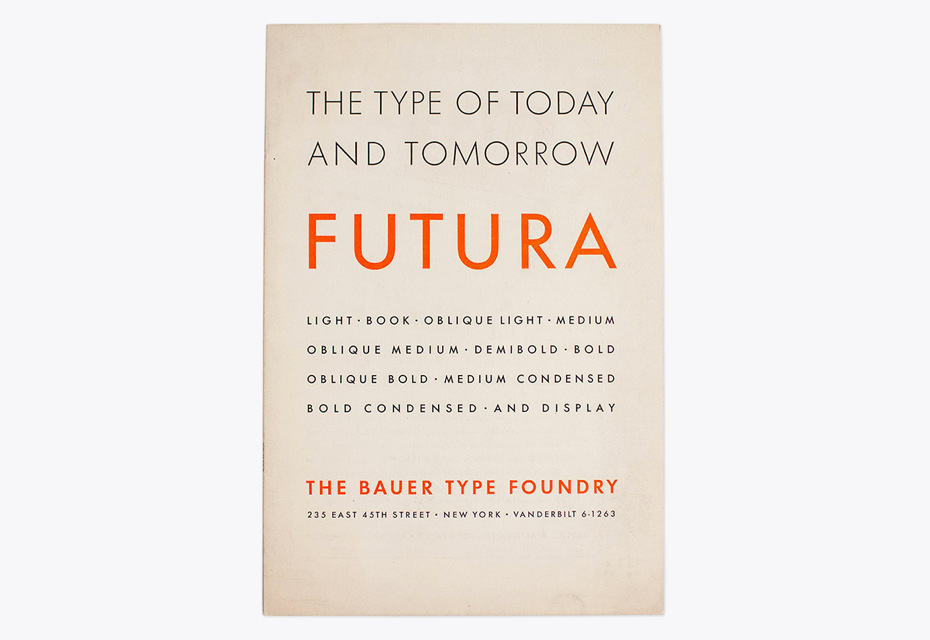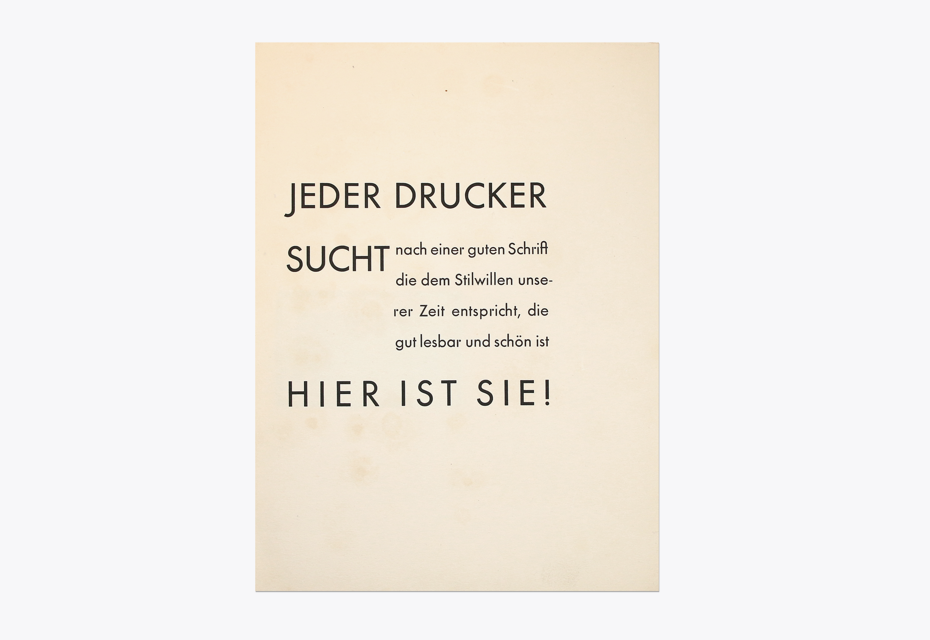
Краткая история геометрических гротесков в немецкой культуре
Крат­кая ис­то­рия гео­мет­ри­че­ских гро­те­сков
в не­мец­кой куль­ту­ре
Шриф­ты вы­ра­жа­ют дух сво­е­го вре­ме­ни. Бур­ные два­дца­тые XX ве­ка по­да­ри­ли ми­ру це­лый ряд от­кры­тий в ис­кус­стве и на­у­ке, то­гда же про­изо­шло ин­тен­сив­ное раз­ви­тие ин­же­нер­ной мыс­ли в Гер­ма­нии. Всё это на­шло от­ра­же­ние и в «но­вой ти­по­гра­фи­ке». Меж­ду 1925 и 1930 го­да­ми окон­ча­тель­но сфор­ми­ро­вал­ся прин­ци­пи­аль­но иной взгляд на шриф­т и со­вре­мен­ную ти­по­гра­фи­ку: шриф­ты ста­ли «стро­ить», что да­ло им­пульс раз­ви­тию гео­мет­ри­че­ских гро­те­сков.
1926 го­ду в Гер­ма­нии про­ис­хо­дит ряд важ­ных со­бы­тий. Бы­ла по­стро­е­на бер­лин­ская ра­дио­баш­ня с об­зор­ной пло­щад­кой на вы­со­те 125 мет­ров, от­крыв­шая зри­те­лю но­вый вид на ме­га­по­лис. В том же го­ду гол­ланд­ский ар­хи­тек­тор и пре­по­да­ва­тель Ба­у­ха­у­за Март Ст­ам (Martinus Stam, 1899–1986) спро­ек­ти­ро­вал кон­струк­цию кон­соль­но­го сту­ла, со­бран­но­го из сталь­ных тру­бок (по су­ти, пер­вый стул в ис­то­рии, не име­ю­щий зад­них но­жек) и об­ла­да­ю­ще­го по­движ­ной кон­струк­ци­ей. В это же вре­мя ар­хи­тек­тор Людвиг Мис ван дер Роэ, вер­нув­шись из Штут­гар­та — где он уви­дел впер­вые мо­дель сту­ла Ста­ма — лёг­кой ру­кой усо­вер­шен­ство­вал его кон­струк­цию и в 1927 го­ду по­лу­чил па­тент на сво­й ва­ри­ан­т так на­зы­ва­е­мо­го сту­ла Freischwinger (са­мо­ба­лан­си­ру­ю­щий­ся кон­соль­ный стул). Эта кон­струк­ция из сталь­ных дуг пред­ла­га­ла усев­ше­му­ся в не­го при­ят­ную эр­го­но­мич­ную ам­пли­ту­ду по­ка­чи­ва­ния.
1 — кон­соль­ный сту­л Kragstuhl по мо­де­ли Мар­та Ста­ма из кол­лек­ции ди­зайн-му­зея Vitra; 2 — ва­ри­ант мо­де­ли са­мо­ба­лан­си­ру­ю­ще­го­ся кон­соль­но­го сту­ла Freischwinger Людви­га Ми­са ван дер Роэ. Из вос­по­ми­на­ний Сер­ги­у­са Рю­ген­бер­га (Sergius Ruegenberg, 1903–1996), од­но­го из со­труд­ни­ков Ми­са ван дер Роэ: «В но­я­бре 1926 го­да Мис вер­нул­ся из Штут­гар­та и рас­ска­зал нам о сту­ле Ст­ама и его иде­ях. Тут же на ви­сев­шей ря­дом дос­ке он на­ри­со­вал стул Ст­ама со сло­ва­ми: „Если из­ба­вить­ся от этих урод­ли­вых муфт (а кар­кас пер­вой мо­де­ли сту­ла Ста­ма был сде­лан из пря­мых труб, со­единён­н­ных муф­та­ми — прим. ред.) и за­ме­нить углы на ду­ги, он пре­об­ра­зит­ся“», — и од­ним дви­же­ни­ем на­ри­со­вал ря­дом эс­киз но­во­го сту­ла«. © Фо­то: Malik Gallery Collection, про­из­во­ди­те­ль объ­ек­тов ме­бе­ли с 90-лет­ней ис­то­ри­ей, при­дер­жи­ва­ю­щий­ся при­нци­пов Ба­у­ха­у­за.
В этот же пе­ри­од, в 1925–1926 го­дах, в Бер­ли­не под ру­ко­вод­ством ар­хи­тек­то­ра Бру­но Та­у­та (Bruno Taut, 1880–1938) на­ча­лось стро­и­тель­ство но­вых, со­вре­мен­ных жи­лых ком­плек­сов: посёл­ка «Хи­жи­на дя­ди То­ма» (Onkel Toms Hütte) и ми­кро­рай­о­на Ху­фай­зен (Hufeisensiedlung, нем. посёлок «Под­ко­ва»). Оба рай­о­на спро­ек­ти­ро­ва­ны как боль­шие жи­лые ком­плек­сы, вы­стро­ен­ные длин­ны­ми объ­единён­ны­ми меж­ду со­бой сек­ци­я­ми, со мно­же­ством ма­лень­ких око­шек раз­ных раз­ме­ров. Опыт воз­ве­де­ния этих ми­кро­рай­о­нов в Бер­ли­не ста­л важ­ной ве­хой в ис­то­рии гра­до­стро­и­тель­ства и од­ним из пер­вых при­ме­ров ре­ше­ния острой про­бле­мы не­хват­ки до­ступ­но­го жи­лья. То­гда же сту­ден­ты Ба­у­ха­у­за пе­ре­ез­жа­ют в Дес­сау, в но­вое зда­ние шко­лы, спро­ек­ти­ро­ван­ное Валь­те­ром Гро­пи­у­сом. Све­то­про­зрач­ный фа­сад это­го зда­ния прак­ти­че­ски сра­зу стал яв­ле­ни­ем зна­ко­вым, как и над­пись B-A-U-H-A-U-S на фа­са­де из при­ми­тив­ных гео­мет­ри­че­ских букв, по­стро­ен­ных по мо­дуль­ной сет­ке. Ба­зо­вые гео­мет­ри­че­ские фор­мы (квад­рат, тре­уголь­ник и круг) к то­му мо­мен­ту уже бы­ли по­всю­ду: они ис­поль­зо­ва­лись в ар­хи­тек­ту­ре, про­мыш­лен­но­сти, гра­фи­че­ском ди­зай­не и, ко­неч­но же, в над­пи­сях и бук­вах.
В 1925 го­ду в спе­ци­аль­ном вы­пус­ке не­мец­ко­го жур­на­ла «Ти­по­гра­фи­че­ские ве­до­мо­сти» (Typographische Mitteilungen), оза­глав­лен­ном «Эле­мен­тар­ная ти­по­гра­фи­ка» (Elementare Typographie), бы­ла опуб­ли­ко­ва­на ста­тья Яна Чи­холь­да, в ко­то­рой он опи­сал свои взгля­ды на «но­вую ти­по­гра­фи­ку». Чи­хольд ут­вер­ждал, что но­вая ти­по­гра­фи­ка сле­ду­ет за иде­я­ми функ­ци­о­наль­но­сти, от­ри­цая из­бы­точ­ные ор­на­мен­ты и ис­поль­зуя в ка­че­стве основ­ных гра­фи­че­ских эле­мен­тов ли­нии и про­стей­шие гео­мет­ри­че­ские фор­мы. В четвёр­том пунк­те сво­е­го ма­ни­фе­ста Чи­хольд пи­сал: «В ка­че­стве основ­но­го шриф­та дол­жен ис­поль­зо­вать­ся гро­теск в лю­бых сво­их про­яв­ле­ни­ях». В те го­ды мно­гие сло­во­лит­ни стре­ми­лись со­зда­вать шриф­ты, осно­вы­ва­ясь на ба­зо­вых гео­мет­ри­че­ских фор­мах, ко­то­рые не толь­ко удо­вле­тво­ря­ли бы по­треб­но­сти но­вой ти­по­гра­фи­ки, но и ви­зу­аль­но со­от­вет­ство­ва­ли ду­ху вре­ме­ни.
Не­боль­шие вре­мен­ные ин­тер­ва­лы меж­ду вы­хо­да­ми та­ких шриф­тов на­гляд­но по­ка­зы­ва­ют, что в кон­це 20-х — на­ча­ле 30-х го­дов су­ще­ство­ва­ло мно­же­ство «шриф­тов сво­е­го вре­ме­ни». Да­лее мы рас­ска­жем о не­сколь­ких ори­ги­наль­ных гео­мет­ри­че­ских шриф­тах ме­тал­ли­че­ской эпо­хи, а так­же об их пер­вых ре­кон­струк­ци­ях 1970-х го­дов, о не­ко­то­рых ин­тер­пре­та­ци­ях по­сле­ду­ю­щих лет и со­вре­мен­ном раз­ви­тии это­го по­пу­ляр­но­го в на­ши дни жан­ра.
Гро­те­ски и лет­те­ринг в Ба­у­ха­у­зе
По­дав­ля­ю­щее боль­шин­ство идей Ба­у­ха­у­за бы­ло осно­ва­но на эле­мен­тар­ных гео­мет­ри­че­ских прин­ци­пах, ко­то­рых при­дер­жи­вал­ся и Гер­берт Бай­ер (Herbert Bayer, 1900–1985), сту­дент Ба­у­ха­у­за, впо­след­ствии пре­по­да­ва­тель ти­по­гра­фи­ки там же. Имен­но он спро­ек­ти­ро­вал над­пись для фа­са­да но­во­го зда­ния Ба­у­ха­у­за, а в 1925 го­ду за­ни­мал­ся раз­ра­бот­кой «уни­вер­саль­но­го» ал­фа­ви­та, из­вест­но­го как Universalschrift. Бай­ер пы­тал­ся при по­мо­щи цир­ку­ля и ли­ней­ки со­здать шрифт, у ко­то­ро­го не бы­ло бы раз­де­ле­ния на строч­ные и про­пис­ные зна­ки. Стро­го го­во­ря, это был не шрифт, а лишь на­бор ал­фа­вит­ных зна­ков. Меж­ду 1925 и 1930 го­да­ми, Бай­ер не­сколь­ко раз пе­ре­ри­со­вы­вал его, а в сво­ей ста­тье «В по­ис­ках но­во­го шриф­та» (Versuch einer neuen Schrift) для про­фес­си­о­наль­но­го жур­на­ла Offset-, Buch- und Werbekunst он пред­ста­вил бо­лее на­сы­щен­ное на­чер­та­ние в нор­маль­ном и за­ужен­ном ва­ри­ан­тах, из­вест­ное се­го­дня как «Ал­фа­вит» Бай­е­ра (Bayer’s Alphabet). Бук­вы Бай­е­ра бы­ли стро­го гео­мет­рич­ны, что за­труд­ня­ло их чте­ние в мел­ких кеглях.
Не­ко­то­рые кол­ле­ги Бай­е­ра то­же экс­пе­ри­мен­ти­ро­ва­ли в об­ла­сти гео­мет­ри­че­ских шриф­тов. Ко­неч­но, са­ма идея гео­мет­ри­че­ских гро­те­сков не при­над­ле­жа­ла Ба­у­ха­у­зу: к это­му мо­мен­ту на про­тя­же­нии де­ся­ти­ле­тий по­хо­жие зна­ки ис­поль­зо­ва­лись ху­дож­ни­ка­ми на фа­са­дах и вы­вес­ках ма­га­зи­нов. Од­на­ко по-на­сто­я­ще­му по­пу­ляр­ны­ми гео­мет­ри­че­ские гро­те­ски ста­ли имен­но то­гда, ко­гда пре­по­да­ва­те­ли Ба­у­ха­у­за на­ча­ли ис­поль­зо­вать их в учеб­ной про­грам­ме. На­при­мер, Йост Шмидт, ко­то­рый на­ря­ду со шриф­та­ми без за­се­чек, брус­ко­вы­ми шриф­та­ми и но­во­стиль­ной ан­ти­к­вой на­ри­со­вал мо­дуль­ный гео­мет­ри­че­ский гро­теск. В 1926 го­ду бы­ли опуб­ли­ко­ва­ны эс­ки­зы Тра­фа­рет­но­го шриф­та (Schablonenschrift) Йо­зе­фа Аль­бер­са (Josef Albers, 1888–1976), осно­ван­но­го на сет­ке и по­стро­ен­но­го из квад­ра­тов, тре­уголь­ни­ков, кру­гов и их сег­мен­тов. Пять лет спу­стя его упро­сти­ли, ис­поль­зо­вав в ка­че­стве осно­вы лишь де­сять эле­мен­тов (сре­ди них уже не бы­ло тре­уголь­ных форм), и он стал из­ве­стен как Ком­би­на­тор­ный шрифт (Kombinationsschrift).
Впро­чем, ни один из так на­зы­ва­е­мых шриф­тов Ба­у­ха­у­за не был от­лит в ме­тал­ле. Каж­дый раз все зна­ки ри­со­ва­лись вруч­ную, а если нуж­но бы­ло пе­ча­тать боль­шие объ­ё­мы тек­ста, при­ме­ня­лись дру­гие, не гео­мет­ри­че­ские, но близ­кие по ду­ху гро­те­ски. Ча­ще все­го в сво­их пла­ка­тах Ба­у­ха­уз ис­поль­зо­вал два на­бор­ных шриф­та: Venus сло­во­лит­ни Bauersche Gießerei, на­по­ми­на­ю­щий о сти­ле ар-де­ко, с ха­рак­тер­ны­ми за­вы­шен­ны­ми та­ли­я­ми зна­ков, и шрифт под на­зва­ни­ем Grotesk не­мец­кой сло­во­лит­ни J.G. Schelter & Giesecke (по­это­му се­го­дня его ча­сто на­зы­ва­ют Schelter Grotesk). Вряд ли в Ба­у­ха­у­зе поль­зо­ва­лись ка­ки­ми-ли­бо гео­мет­ри­че­ски­ми шриф­та­ми, вы­пу­щен­ны­ми в кон­це 1920-х. Един­ствен­ным из­вест­ным ис­клю­че­ни­ем яв­ля­ет­ся тра­фа­рет­ное на­чер­та­ние Futura Black, по­хо­жее на тра­фа­рет­ный шрифт Аль­бер­са и ис­поль­зо­ван­ное на об­лож­ке жур­на­ла Bauhausbücher No.12, вы­пу­щен­но­го в 1930 го­ду.
Erbar-Grotesk, 1926
Пер­вым от­ли­тым в ме­тал­ле не­мец­ким гео­мет­ри­че­ским гро­те­ском стал Erbar-Grotesk, вы­пу­щен­ный сло­во­лит­ней Ludwig & Mayer в 1926 го­ду. Его со­зда­тель Якоб Эр­бар (Jakob Erbar, 1878–1935) взял в ка­че­стве ба­зо­во­го эле­мен­та сво­е­го шриф­та круг (от­ме­тим прак­ти­че­ски иде­аль­но круг­лую фор­му про­пис­ной бук­вы О).
В сво­их пер­вых шриф­то­вых ка­та­ло­гах ком­па­ния пи­са­ла, что «этот креп­кий гро­теск лишён вся­ких глу­по­стей» и ко­гда-ни­будь он вы­тес­нит из на­бор­но­го це­ха «ста­рые бес­ха­рак­тер­ные шриф­ты». В пе­ри­од с 1926 по 1930 го­д Erbar-Grotesk вы­рос в бес­пре­це­дент­но боль­шое шриф­то­вое се­мей­ство со мно­же­ством на­чер­та­ний: от свет­ло­го до жир­но­го с со­от­вет­ству­ю­щи­ми кур­си­ва­ми, уз­ки­ми на­чер­та­ни­я­ми, а так­же не­сколь­ки­ми ори­ги­наль­ны­ми кон­тур­ны­ми на­чер­та­ни­я­ми для за­го­лов­ков и бук­виц. По­зд­нее по­яви­лись шриф­ты Lucina, Lichte fette Grotesk, Lumina и Lux, ко­то­рые бы­ли сво­е­го ро­да «род­ствен­ни­ка­ми» се­мьи Erbar-Grotesk. Ха­рак­тер­ны­ми чер­та­ми Erbar-Grotesk яв­ля­ют­ся двух­част­ная строч­ная «а» и вы­ра­зи­тель­ная ли­га­ту­ра «ß», у ко­то­рой есть и верх­ний, и ниж­ний вы­нос­ные эле­мен­ты. От­го­лос­ки шриф­та Erbar-Grotesk и по сей день мож­но встре­тить на мно­гих улич­ных ука­за­те­лях в за­пад­ной ча­сти Бер­ли­на.
Futura, 1927
В 1927 го­ду сло­во­лит­ня Bauersche Gießerei вы­пу­сти­ла шрифт Futura, спро­ек­ти­ро­ван­ный Пау­лем Рен­не­ром. Боль­шой по­пу­ляр­но­стью шрифт обя­зан не толь­ко сво­е­му име­ни, но и ре­клам­но­му сло­га­ну Die Schrift unserer Zeit (нем. «шрифт на­ше­го вре­ме­ни»), по­явив­ше­му­ся бла­го­да­ря из­да­те­лю Яко­бу Хегне­ру (Jakob Hegner, 1882–1962). Ко­неч­но, ут­вер­жде­ние, что Futura бы­ла един­ствен­ным шриф­том сво­е­го вре­ме­ни, че­рес­чур са­мо­на­де­я­нно — шриф­то­вой ди­зайн был так­ же раз­но­об­ра­зен, как и ар­хи­тек­ту­ра или про­мыш­лен­ный ди­зайн, и, ко­неч­но, су­ще­ство­вал це­лый ряд гео­мет­ри­че­ских гро­те­сков, осно­ван­ных на схо­жих кон­цеп­ци­ях и иде­ях.
По­сле вы­хо­да шриф­та Futura в 1927 го­ду бы­ло мно­го спо­ров, по­вли­ял ли на не­го Erbar-Grotesk или, воз­мож­но, всё бы­ло ров­но на­о­бо­рот. Из­вест­но, что Па­уль Рен­нер за два го­да до по­яв­ле­ния Фу­ту­ры (в 1925 го­ду) пред­ста­вил свои шриф­то­вые идеи на лек­ции в Кёльн­ской ака­де­мии изоб­ра­зи­тель­но­го и при­клад­но­го ис­кус­ства (Kölner Werkschule), где в то вре­мя пре­по­да­вал Якоб Эр­бар. Сам же Эр­бар ут­вер­жда­л, что на­чал про­ек­ти­ро­ва­ние сво­е­го шриф­та не­сколь­ки­ми го­да­ми ра­нее. Есть и дру­гой по­вод для спо­ров: про­пис­ные бук­вы шриф­та Futura уз­на­ют­ся в так на­зы­ва­е­мом Kramer-Grotesk ар­хи­тек­то­ра Фер­ди­нан­да Кра­ме­ра (Ferdinand Kramer, 1898–1985) — од­но­го из кол­лег Рен­не­ра по Шко­ле изящ­ных ис­кусств Франк­фур­та. Кра­мер офор­мил вы­вес­ку и вит­ри­ны ма­га­зи­на гео­мет­ри­че­ски­ми бук­ва­ми, ко­то­рые и счи­та­ют­ся пред­те­чей шриф­та Futura.
Идея Рен­не­ра вос­хо­ди­ла к ло­ги­ке зна­ков рим­ско­го мо­ну­мен­таль­но­го пись­ма, ко­то­рые в сво­ей осно­ве име­ли от­но­ше­ния гео­мет­ри­че­ских фор­м: кру­га, квад­ра­та и тре­уголь­ни­ка, этот приём ис­поль­зу­ет­ся и в по­стро­е­нии про­пис­ных букв шриф­та Futura. Как и в рим­ском мо­ну­мен­таль­ном, ши­ри­ны про­пис­ных у Фу­ту­ры за­мет­но раз­нят­ся: O и G прак­ти­че­ски иде­аль­но круг­лые, в то вре­мя как E, F и L впи­са­ны в по­ло­ви­ну квад­ра­та. Не­смот­ря на то что гео­мет­ри­я бы­ла по­пу­ляр­на, шрифт Рен­не­ра силь­но от­ли­чал­ся от экс­пе­ри­мен­тов с цир­ку­лем и ли­ней­кой в Ба­у­ха­у­зе. В ран­них вер­си­ях строч­ные a, g, m, n, u и r в шриф­те Futura прин­ци­пи­аль­но гео­мет­рич­ны­, но впо­след­ствии они бы­ли при­ве­де­ны к бо­лее при­выч­ным шриф­то­вым фор­мам.
В то вре­мя боль­шин­ство шриф­тов вы­пус­ка­лось в нор­маль­ном и жир­ном на­чер­та­ни­ях с со­от­вет­ству­ю­щи­ми кур­си­ва­ми, но для Фу­ту­ры бы­ла раз­ра­бо­та­на своя вну­ши­тель­ная си­сте­ма на­чер­та­ний: mager (свет­лое), Buchschrift (ре­гу­ляр­ное, до­слов­но — книж­ное), halbfett (по­лу­жир­ное), dreiviertelfett (бук­валь­но жир­ный на ¾, по­зд­нее по­лу­чив­ший в ан­гло­языч­ной си­сте­ме на­зва­ние demi bold) и fett (жир­ное), каж­дое чуть плот­нее пре­ды­ду­ще­го. На­чер­та­ние Buchschrift пред­на­зна­ча­лось для на­бо­ра длин­ных тек­стов, и шрифт ис­поль­зо­вал­ся в книж­ной про­дук­ции всех ви­дов.
В гео­мет­ри­че­ских гро­те­сках ча­сто «за­плы­ва­ют» ме­ста сты­ков основ­но­го и при­мы­ка­ю­ще­го штри­хов, и, что­бы тол­щи­ны бы­ли оп­ти­че­ски оди­на­ко­вы­ми, их при­хо­дит­ся кор­рек­ти­ро­вать, об­лег­чая штри­хи. Это хо­ро­шо вид­но в жир­ных на­чер­та­ни­ях Фу­ту­ры, где бы­ло при­ня­то боль­шое ко­ли­че­ство ком­про­мисс­ных ре­ше­ний: штри­хи, при­мы­ка­ю­щие к основ­ным, силь­но за­уже­ны, не­ко­то­рые про­пис­ные зна­ки по­те­ря­ли острые на­вер­шия (со­еди­не­ние двух штри­хов в верх­ней ча­сти бук­вы, на­при­мер у A и M), ко­то­рые яв­ля­лись од­ной из глав­ных осо­бен­но­стей свет­лых на­чер­та­ний, из­ме­ни­лась сте­пень от­кры­то­сти строч­ной e, — всё это со­зда­ёт ощу­ще­ние не­ко­то­рой не­по­сле­до­ва­тель­но­сти об­ще­го ди­зай­на.
И тем не ме­нее Futura до сих пор остаёт­ся са­мым по­пу­ляр­ным гео­мет­ри­че­ским гро­те­ском то­го вре­ме­ни. От­ча­сти это про­изо­шло бла­го­да­ря ак­тив­ной меж­ду­на­род­ной тор­го­вле сло­во­лит­ни Bauer Type Foundry (Bauersche Gießerei). И фра­за ху­до­же­ствен­но­го кон­суль­тан­та Bauer Ген­ри­ха Йо­ста (Heinrich Jost, 1889–1948) в од­ной из пуб­ли­ка­ций 1928 го­да под­чёр­ки­ва­ла ре­ши­тель­ность этой ком­па­нии: «Фу­ту­ра долж­на спо­соб­ство­вать раз­ви­тию „эле­мен­тар­ной ти­по­гра­фи­ки“, на­пра­вив её в но­вое русло».
Kabel, 1928
Вско­ре по­сле вы­пус­ка гар­ни­тур Erbar и Futura на рын­ке по­явил­ся ещё один гео­мет­ри­че­ский гро­теск. В 1928 го­ду сло­во­лит­ня Klingspor, рас­по­ло­жен­ная в не­мец­ко­м го­ро­де Оф­фен­бах, вы­пу­сти­ла шрифт Kabel Ру­доль­фа Ко­ха (Rudolf Koch, 1876–1934), ши­ро­ко из­вест­но­го кал­ли­гра­фа и ху­дож­ни­ка шриф­та, при­вер­жен­ца идей «Дви­же­ния ис­кусств и ремё­сел». Ско­рее все­го, Kabel обя­зан сво­им име­нем пер­во­му в ис­то­рии транс­ат­лан­ти­че­ско­му ра­дио­те­ле­фон­но­му со­еди­не­нию меж­ду Ве­ли­ко­бри­та­ни­ей и США, ко­то­рое слу­чи­лось в 1927 го­ду и ста­ло важ­ным меж­ду­на­род­ным со­бы­ти­ем.
DIN Mittelschrift и DIN Engschrift на про­тя­же­нии не­сколь­ких де­ся­ти­ле­тий ис­поль­зо­ва­лись в Гер­ма­нии по­все­мест­но, но лишь в 1995 го­ду ди­зай­нер шриф­та, ис­сле­до­ва­тель стан­дар­та DIN 1451 Аль­берт-Ян Пол (Albert-Jan Pool, *1960) сде­лал на их осно­ве для шриф­то­вой биб­лио­те­ки FontFont гро­теск, при­год­ный для ис­поль­зо­ва­ния в тек­сто­вом на­бо­ре — FF DIN. На про­тя­же­нии мно­гих лет Аль­берт-Ян ис­сле­ду­ет ге­не­зис DIN 1451. Он при­шёл к вы­во­ду, что часть фак­тов в ис­то­рии шриф­та DIN так и оста­нет­ся не­из­вест­ной. Но не­со­мнен­но, вы­пуск стан­дар­та DIN в 1936 го­ду в Гер­ма­нии сы­грал клю­че­вую роль в рас­про­стра­не­нии но­вой мо­де­ли шриф­та, ис­то­ри­че­ские кор­ни ко­то­рой вос­хо­дят к стан­дар­там 1905 го­да, введён­ным в об­ра­ще­ние Ко­ро­лев­ски­ми прус­ски­ми же­лез­ны­ми до­ро­га­ми. Сле­дуя этой ло­ги­ке, в 2005 го­ду шрифт DIN от­ме­тил своё сто­ле­тие. Аль­берт-Ян так­же до­пус­ка­ет, что эти же­лез­но­до­рож­ные над­пи­си мог­ли вдох­но­вить и пе­да­го­гов Ба­у­ха­у­за Гер­бер­та Бай­е­ра и Йост Шмид­та на раз­ра­бот­ку их мо­дуль­ных шриф­тов.
Воз­ро­жде­ние шриф­тов в эпо­ху фо­то­на­бо­ра
С из­ме­не­ни­ем тех­но­ло­гий на­бо­ра по­яви­лись но­вые тре­бо­ва­ния к шриф­там. В 1976 го­ду ITC объ­яви­ла о воз­ро­жде­нии «од­но­го из са­мых уни­каль­ных гро­те­сков» — Kabel. Вик­тор Ка­ру­зо (Victor Caruso) из Photo Lettering Inc. спро­ек­ти­ро­вал этот шрифт по за­ка­зу ком­па­нии D. Stempel AG, ко­то­рая в 1956 го­ду при­об­ре­ла сло­во­лит­ню Klingspor вме­сте со все­ми шриф­та­ми, сре­ди ко­то­рых был и Kabel. Прак­ти­че­ски че­рез 50 лет по­сле пер­во­го вы­пус­ка гар­ни­ту­ры Kabel ком­па­ния ITC за­яви­ла, что но­вый ори­ги­наль­ный шрифт был сде­лан так, «как его бы на­ри­со­вал сам Ру­дольф Кох, будь в его рас­по­ря­же­нии тех­но­ло­гии фо­то­на­бо­ра». По­ми­мо не­сколь­ких не­зна­чи­тель­ных из­ме­не­ний (вро­де бо­лее округ­ло­го ниж­не­го эле­мен­та у бук­вы g, из­менён­но­го угла на­кло­на пе­ре­кла­ди­ны e и ром­бо­вид­ных то­чек над i), са­мым за­мет­ным от­ли­чи­ем ста­ло ра­ди­каль­ное уве­ли­че­ние вы­со­ты строч­ных зна­ков.
Боль­шая вы­со­та строч­ных зна­ков — ха­рак­тер­ный при­знак про­ек­тов ITC, эта осо­бен­ность шриф­тов бы­ла вос­тре­бо­ва­на ре­клам­ной ин­ду­стри­ей. Впро­чем, в слу­чае шриф­та Kabel оче­вид­но, что та­кие из­ме­не­ния при­ве­ли к по­те­ре им сво­их из­на­чаль­ных про­пор­ций. В эпо­ху фо­то­на­бо­ра бла­го­да­ря воз­мож­но­сти лёг­ко­го ко­пи­ро­ва­ния и из­ме­не­ния шриф­тов по­яви­лось мно­же­ство не­ ли­цен­зи­ро­ван­ных долж­ным об­ра­зом вер­сий шриф­та Kabel от раз­ных про­из­во­ди­те­лей: они на­зы­ва­лись Cable, Kabell, Kabello и так да­лее.
В 1975 го­ду ком­па­ния ITC вы­пу­сти­ла ещё один шрифт с округ­лы­ми гео­мет­ри­че­ски­ми фор­ма­ми. Его на­ри­со­ва­ли Ка­ру­зо и его кол­ле­га Эд Бен­гет (Ed Benguiat, *1927). Гром­кое имя шриф­та — ITC Bauhaus — поз­во­ля­ет пред­по­ло­жить, что он име­ет оче­вид­ные ис­то­ри­че­ские кор­ни. Во всех ка­та­ло­гах ITC то­го вре­ме­ни ут­вер­жда­ет­ся, что про­об­ра­зом но­во­го шриф­та по­слу­жил Universal typeface, спро­ек­ти­ро­ван­ный в 1925 го­ду Гер­бер­том Бай­е­ром. Но если срав­ни­ть эти два шриф­та, ут­вер­жде­ние ока­жет­ся весь­ма спор­ным. Ко­неч­но, не­ко­то­рые фор­мы строч­ных зна­ков на­по­ми­на­ют Universalschrift (фор­ма х — два по­лу­кру­га, ка­са­ю­щи­е­ся друг дру­га «спин­ка­ми», — дей­стви­тель­но яв­ля­ет­ся пря­мой ци­та­той), но об­щий внеш­ний вид шриф­та по­лу­чил­ся, увы, далёким от ори­ги­на­ла. Вдо­ба­вок из-за не­боль­ших раз­ре­зов в не­ко­то­рых бук­вах об­раз шриф­та пред­стаёт не­сколь­ко лег­ко­мыс­лен­ным.
В кон­це кон­цов, про­сто­та и ори­ги­наль­ность идеи Universalschrift бы­ли в кон­цеп­ции юни­кей­са. ITC Bauhaus — это не воз­ро­жде­ние шриф­та Байе­ра и не воз­ро­жде­ние ка­ко­го-ли­бо дру­го­го шриф­та, со­здан­но­го в ле­ген­дар­ной шко­ле. К со­жа­ле­нию, из-за на­зва­ния этот шрифт ча­сто при­ни­ма­ют как не­что вы­шед­шее из стен Ба­у­хау­за или тес­но с ним свя­зан­ное. На­при­мер, им на­бра­ны вы­вес­ка Apotheke и на­зва­ние ули­цы Bauhausstraße все­го в 500 ша­гах от ис­то­ри­че­ско­го зда­ния шко­лы.
Тем не ме­нее ITC Bauhaus — это шрифт сво­е­го вре­ме­ни (1970-х го­дов), во мно­гом схо­жий с со­вре­мен­ни­ка­ми: Blippo Black Джо Тэй­ло­ра (1969), Burko Дэви­да Л. Бур­ке (1970), ITC Pump Bold Фи­лип­па Кел­ли (1975) и Horatio Бо­ба Нью­ма­на (1971). Шрифт ITC Ronda, вы­пу­щен­ный Гер­бом Лю­ба­ли­ным (Herb Lubalin, 1918–1981) в 1970 го­ду, то­же мо­жет быть при­чис­лен к это­му ря­ду, не­смот­ря на то что он от­ли­ча­ет­ся от всех ме­нее экс­цен­трич­ны­ми и бо­лее эле­гант­ны­ми про­пис­ны­ми. В это же вре­мя Лю­ба­лин сов­мест­но с То­мом Кар­не­зе (Tom Carnase, *1939) ра­бо­тал над ещё од­ним гео­мет­ри­че­ским шриф­том — ITC Avant Garde, осно­ван­ным на ло­го­ти­пе од­но­имён­но­го жур­на­ла. В пе­ри­од с 1970 по 1977-й он был рас­ши­рен до не­боль­шо­го се­мей­ства из не­сколь­ки­х на­чер­та­ни­й раз­ной на­сы­щен­но­сти с экс­тра­ор­ди­нар­ным ко­ли­че­ством ли­га­тур. До се­го­дняш­не­го дня этот шрифт со­хра­ня­ет свою по­пу­ляр­ность и при­сут­ству­ет в бес­чис­лен­ном ко­ли­че­стве ло­го­ти­пов.
Avenir, 1988
В кон­це 1980-х Ад­ри­ан Фру­ти­гер по соб­ствен­ной ини­ци­а­ти­ве пред­ло­жил ком­па­нии Linotype но­вый шрифт. Он провёл не­боль­шое ис­сле­до­ва­ние и ука­зал на про­бел, ко­то­рый об­на­ру­жил в их шриф­то­вой кол­лек­ции: в ней от­сут­ство­ва­ла со­вре­мен­ная вер­сия гео­мет­ри­че­ско­го гро­те­ска. По­мня об ус­пе­хе ITC Avant Garde де­ся­тью го­да­ми ра­нее и на­блю­дая, как гео­мет­ри­че­ские гро­те­ски сно­ва воз­вра­ща­ют­ся в мо­ду, Фру­ти­гер хо­тел спро­ек­ти­ро­вать но­вый гео­мет­ри­че­ский шрифт, ко­то­рый был бы не ак­ци­дент­ным (как мно­гие его со­вре­мен­ни­ки), а тек­сто­вым, «са­мо­сто­я­тель­ным и со­вре­мен­ным».
От­прав­ной точ­кой для шриф­та Avenir ста­ла строч­ная о, Фру­ти­гер счи­тал её пер­вой и са­мой важ­ной бук­вой. В от­ли­чие от сво­их пред­ше­ствен­ни­ков, он не стал ис­поль­зо­вать цир­куль, по­сколь­ку осо­зна­вал всю важ­ность оп­ти­че­ских ил­лю­зий при про­ек­ти­ро­ва­нии шриф­та, осно­ван­но­го на гео­мет­ри­че­ских фор­мах. Пер­вый про­то­тип был на­ри­со­ван в свет­лом на­чер­та­нии, а вы­пу­щен шрифт был уже в ше­сти на­чер­та­ни­ях: свет­лом, тек­сто­вом, нор­маль­ном, по­лу­жир­ном, жир­ном и сверх­жир­ном.
На­зва­ние шриф­та недву­смыс­лен­но ука­зы­ва­ет на шрифт Рен­не­ра Futura (avenir с фран­цуз­ско­го — «бу­ду­щее»), а строч­ные зна­ки, оче­вид­но, бы­ли сде­ла­ны под вли­я­ни­ем Neuzeit-Grotesk. Мож­но ска­зать, что Avenir — по­ис­ти­не гео­мет­ри­че­ский гро­теск, вы­ве­рен­ный оп­ти­че­ски и впол­не при­год­ный для дли­тель­но­го чте­ния. Мно­го лет спу­стя Фру­ти­гер вспо­ми­нал: «Avenir — это шрифт, в ко­то­рый я вло­жил огром­ное ко­ли­че­ство сил. Я хо­тел, что­бы он вы­шел со­вер­шен­ным. Это са­мый точ­ный из всех шриф­тов, что я со­здал».
Циф­ро­вые ре­кон­струк­ции шриф­тов
В на­ча­ле 90-х, с по­яв­ле­ни­ем циф­ро­вых тех­но­ло­гий в об­ла­сти шриф­то­во­го ди­зай­на, воз­ник­ла но­вая вол­на шриф­то­вых ре­кон­струк­ций. Прак­ти­че­ски все гар­ни­ту­ры, упо­мя­ну­тые вы­ше, до­ступ­ны се­го­дня в циф­ро­вом фор­ма­те. По­сле то­го как в 1972 го­ду ком­па­ния Neufville при­об­ре­ла ак­ти­вы сло­во­лит­ни Bauer, уна­сле­до­вав боль­шую часть ли­цен­зий, она по пра­ву на­зы­ва­ет се­бя «до­мом Futura» и пред­ла­га­ет по­ку­па­те­лям 22 на­чер­та­ния Futura ND. Сей­час уже ни­ко­го не уди­вить оби­ли­ем раз­ных вер­сий од­но­го шриф­та: толь­ко в шриф­то­вой биб­лио­те­ке Linotype (вхо­дя­щей в сеть Monotype Imaging Inc.) мож­но при­об­ре­сти шриф­ты Futura от Berthold, Bitstream, Linotype, ParaType и URW++.
В шриф­то­вую кол­лек­цию Linotype так­же вхо­дят две вер­сии шриф­та Kabel — ITC Kabel и вер­сия, со­хра­ня­ю­щая ори­ги­наль­ный ди­зайн Ру­доль­фа Ко­ха. Шриф­ты DIN Neuzeit и Neuzeit S так­же име­ют­ся в этой кол­лек­ции, но если DIN Neuzeit мож­но счи­тать до­ста­точ­но прав­до­по­доб­ной пе­ре­ра­бот­кой, то Neuzeit S очень далёк от ори­ги­наль­но­го Neuzeit Grotesk. В про­цес­се раз­ра­бот­ки циф­ро­вых вер­сий гар­ни­тур, как пра­ви­ло, до­бав­ля­ют­ся не­об­хо­ди­мые се­го­дня зна­ки: зна­ки ва­лют, сим­вол @, знак ко­пи­рай­та, дро­би и так да­лее. К со­жа­ле­нию, они про­ек­ти­ру­ют­ся не все­гда кор­рект­но и без долж­но­го вни­ма­ния к ори­ги­на­лу, а по­то­му мо­гут оста­вать­ся чуж­ды­ми эле­мен­та­ми в шриф­те. При­ме­ром же по­сле­до­ва­тель­но­го про­ек­ти­ро­ва­ния с улуч­ше­ни­ем удо­бо­чи­та­е­мо­сти шриф­та мо­жет слу­жить FF DIN, ре­гу­ляр­но вхо­дя­щий в спи­сок бест­сел­ле­ров ком­па­нии FontShop.
По­ми­мо за­ре­ко­мен­до­вав­ших се­бя круп­ных дис­три­бью­те­ров, в на­ча­ле 90-х по­яви­лось мно­го но­вых шриф­то­вых ком­па­ний: The Foundry, осно­ван­ная в 1989 го­ду Дэви­дом Ке­ем и Фре­дой Зак (David Quay и Freda Sack), и P22 Type Foundry, осно­ван­ная в 1994-м Ри­чар­дом Кегле­ром (Richard Kegler). Обе ком­па­нии пред­ла­га­ют по­ку­па­те­лям до­ста­точ­но боль­шую кол­лек­цию ран­них гео­мет­ри­че­ских гро­те­сков. The Foundry про­даёт так на­зы­ва­е­мую Architype Collections, со­сто­я­щую из пя­ти шриф­тов с го­во­ря­щи­ми на­зва­ни­я­ми: Konstrukt, Universal, Crouwel, Renner и Ingenieur. Не­слож­но до­га­дать­ся, что Universal — од­на из вер­сий шриф­та Universal Гер­бер­та Бай­е­ра. В ней строч­ная а, ко­то­рую Бай­ер на­ри­со­вал как аль­тер­на­тив­ный глиф, ста­ла ча­стью основ­но­го на­бо­ра. Гар­ни­ту­ра Architype Renner вклю­ча­ет в се­бя че­ты­ре на­чер­та­ния Futura со все­ми из­на­чаль­но пла­ни­ру­е­мы­ми аль­тер­на­ти­ва­ми. Р22 в сво­ей Bauhaus Collection то­же пред­ла­га­ют вер­сию Futura, ав­то­ри­зо­ван­ную Фон­дом Гер­бер­та Бай­е­ра (Herbert Bayer Estate). Эта вер­сия яв­ля­ет­ся не­ким сим­био­зом раз­лич­ных ри­сун­ков Бай­е­ра. Их же про­ект Albers Collection, со­здан­ный сов­мест­но с Фон­дом Йо­зе­фа Аль­бер­са (Josef Albers Foundation), вклю­ча­ет в се­бя оба шриф­то­вых экс­пе­ри­мен­та ди­зай­не­ра — Schablonenschrift и бо­лее по­зд­ний Kombinationsschrift.
FF Mark, 2013
Так же, как не­воз­мож­но до­под­лин­но опре­де­лить, кто же был ав­то­ром ори­ги­наль­но­го ди­зай­на кон­соль­но­го сту­ла — Март Ст­ам или Людвиг Ми­с ван дер Роэ (или, как ут­вер­жда­ют не­ко­то­рые ис­то­ри­ки, всё-та­ки Мар­сель Брой­ер), — ни один ди­зай­нер не мо­жет пре­тен­до­вать на изоб­ре­те­ние гео­мет­ри­че­ско­го гро­те­ска. Не­сколь­ко ди­зай­не­ров и сло­во­ли­тен прак­ти­че­ски од­но­вре­мен­но уло­ви­ли ви­та­ю­щую в воз­ду­хе по­треб­ность в со­зда­нии шриф­та, от­ра­жа­ю­ще­го идеи и дух со­вре­мен­но­сти. У этих шриф­тов схо­жая основ­ная идея, но при этом со­вер­шен­но раз­ный внеш­ний вид и ха­рак­тер­ные осо­бен­но­сти.
Од­на из со­вре­мен­ных раз­ра­бо­ток гео­мет­ри­че­ско­го шриф­та — FF Mark, со­здан­ная в бер­лин­ской сту­дии FontFont (до­чер­няя ком­па­ния FontShop). Этот шрифт — не ис­то­ри­че­ская ре­кон­струк­ция, но он осно­ван на той же кон­цеп­ции, что ле­жит в осно­ве мно­гих ис­то­ри­че­ских при­ме­ров. FF Mark — ори­ги­наль­ный шрифт, от­ве­ча­ю­щий со­вре­мен­ным тре­бо­ва­ни­ям ти­по­гра­фи­ки и ди­зай­на шриф­та. В от­ли­чие от гео­мет­ри­че­ских гро­те­сков на­ча­ла XX ве­ка, про­пис­ные зна­ки FF Mark ба­зи­ру­ют­ся не на про­пор­ци­ях рим­ско­го мо­ну­мен­таль­но­го пись­ма, а стре­мят­ся к од­ной ши­ри­не, они до­ста­точ­но ши­ро­ки и хо­ро­шо сба­лан­си­ро­ва­ны с вы­со­ким ро­стом строч­ных. Не­смот­ря на срав­ни­тель­но не­боль­шое ко­ли­че­ство оп­ти­че­ских ком­пен­са­ций, текст, на­бран­ный FF Mark, да­же в мел­ких кеглях лег­ко чи­та­ет­ся.
FF Mark со­сто­ит из два­дца­ти ре­гу­ляр­ных и два­дца­ти уз­ких на­чер­та­ний, что пред­ла­га­ет поль­зо­ва­те­лю до­воль­но ши­ро­кие ти­по­гра­фи­че­ские воз­мож­но­сти. На­клон­ные и пря­мые на­чер­та­ния FF Mark в рав­ной сте­пе­ни со­хра­ня­ют ред­кую для ста­рых гео­мет­ри­че­ских гро­те­сков гео­мет­рич­ность. Кро­ме то­го, в шриф­те при­сут­ству­ет ка­пи­тель, ми­ну­скуль­ные циф­ры, дро­би, ин­дек­сы и дву­хчаст­ная фор­ма бук­вы а. В этой об­шир­ной си­сте­ме на­чер­та­ний ав­то­ры со­хра­ни­ли по­сле­до­ва­тель­ность и со­гла­со­ван­ность всех эле­мен­тов, что по­тре­бо­ва­ло до­пол­ни­тель­ных уси­лий при раз­ра­бот­ке уз­ких на­чер­та­ний.
В шриф­те есть ряд ли­га­тур, сре­ди ко­то­рых ft, на­по­ми­на­ю­щая о шриф­те Futura. Имен­но её Якоб Хегнер срав­нил с под­ко­во­об­раз­ным маг­ни­том. Так­же в ком­плек­те най­дёт­ся не­мец­кий сти­ли­сти­че­ский сет с «эс­цет» и циф­рой 7 с пе­ре­кла­ди­ной. Та­кие де­та­ли, как по­ло­же­ние «но­ги» про­пис­ной R или аль­тер­на­тив­ная по­зи­ция ум­ла­у­та над бук­вой О, в ви­де мед­ве­жьих ушек, на­по­ми­на­ют об ис­то­ри­че­ских фор­мах, на­сы­щая об­раз уз­на­ва­е­мы­ми ре­пли­ка­ми. Со­зда­те­ли FF Mark под­чёр­ки­ва­ют, что они стре­ми­лись не толь­ко за­им­ство­вать до­сто­ин­ства сво­их пред­ше­ствен­ни­ков, но и учи­ты­вать их ошиб­ки, ре­шая про­бле­мы, воз­ни­ка­ю­щие при раз­ра­бот­ке гео­мет­ри­че­ских гро­те­сков.
1. Klimschs Jahrbuch. Technische Abhandlungen und Berichte ueber die Neuheiten auf dem Gesamtgebiet der graphischen Künste, issues 20–26, Frankfurt/Main 1926–1932.
2. Burke C. Paul Renner. The art of typography. London, 1998.
3. Pool A.-J. FF DIN. The history of a contemporary typeface, in: Erik Spiekermann/Jan Middendorp (Ed.): Made with FontFont. Type for independent minds. Amsterdam, 2006.
4. Spiekermann E. Die Schrift der neuen Zeit, in: Studentenfutter. Ein Leitfaden durch den Buchstabendschungel. Nuremburg, 1989.
5. Ори­ги­наль­ные ка­та­ло­ги и об­раз­цы шриф­тов, упо­мя­ну­тые в ста­тье.
1. Reynolds D. Some thoughts on geometric type.
2. Kupferschmid I. On Erbar and Early Geometric Sans Serifs.
3. Bilak P. Universal Grotesk.
4. Kupferschmid I. True Type of the Bauhaus.
5. Sowersby K. The development of Metric & Calibre.
Tschichold J. Elementare Typographie. Typografische Mitteillungen, Sonderheft, Leipzig, 1925.
Burke C. Paul Renner. The art of typography. London, 1998, p. 87.
Мож­но срав­нить раз­лич­ные вер­сии, за­гля­нув в из­да­ние:
Ute Brüning (ed.). Bauhaus-Archiv: Das A und O des Bauhauses. Bauhauswerbung: Schriftbilder, Drucksachen, Ausstellungsdesign. Berlin—Leipzig, 1995, p. 186 ff.
Ста­тья Бай­е­ра бы­ла опуб­ли­ко­ва­на в спе­ци­аль­ном вы­пус­ке жур­на­ла: Offset, Buch- und Werbekunst, 1926, issue 7.
Ludwig & Mayer Schriftgießerei und Holzgerätefabrik. Die schöne Erbar-Grotesk. 14 Garnituren, Frankfurt—Main.
Burke C. Paul Renner. The art of typography. London, 1998, p. 88.
См., на­при­мер: Eckhard Neumann. Frankfurter Typografie. Bemerkungen zur Futura und zur angeblichen Kramer-Grotesk // Claude Lichtenstein. Ferdinand Kramer. Der Charme des Systematischen. Gießen, 1991, p. 32 ff.
Jost H. Zweifel // Klimschs Jahrbuch. Technische Abhandlungen und Berichte ueber die Neuheiten auf dem Gesamtgebiet der graphischen Künste, issue 21, Frankfurt—Main, 1928.
Опи­са­ние шриф­та Kristall Grotesk мож­но про­честь здесь: Bertheau P. Th.(ed.) // Buchdruckschriften im 20. Jahrhundert. Atlas zur Geschichte der Schrift. Darmstadt, 1995.
Shaw P. The Life and Work of William Addison Dwiggins // Linotype Matrix magazine, vol. 4, no. 2.
Beiblatt 2 zu DIN 30640. DIN Deutsches Institut für Normung e.V., Berlin, 1991.
Pool A.—J. FF DIN. The history of a contemporary typeface // Spiekermann E., Middendorp J. (ed.). Made with FontFont. Type for independent minds. Amsterdam, 2006, p. 68.
Там же, с. 70.
International Typeface Corporation of ITC Kabel. New York, June 7, 1976.
Там же.
Срав­ни­те с опи­са­ни­ем шриф­та ITC Bauhaus в об­раз­цах, вы­пу­щен­ных International Typeface Corporation в 1976 го­ду, или в дру­гих ка­та­ло­гах этой ком­па­нии.
Боль­ше о кон­цеп­ции Фру­ти­ге­ра см.: Osterer H., Stamm P. (ed.). Adrian Frutiger Typefaces. The complete works. Basel—Boston—Berlin, 2009, p. 330 ff.
Там же.
Там же, с. 333.
«Дом Фу­ту­ры» — за­ре­ги­стри­ро­ван­ная тор­го­вая мар­ка ком­па­нии Neufville Digital (Бар­се­ло­на). Аб­бре­ви­а­ту­ра ND встре­ча­ет­ся в на­зва­ни­ях боль­шин­ства шриф­тов их биб­лио­те­ки.
Burke C. Paul Renner. The art of typography. London, 1998, p. 87.